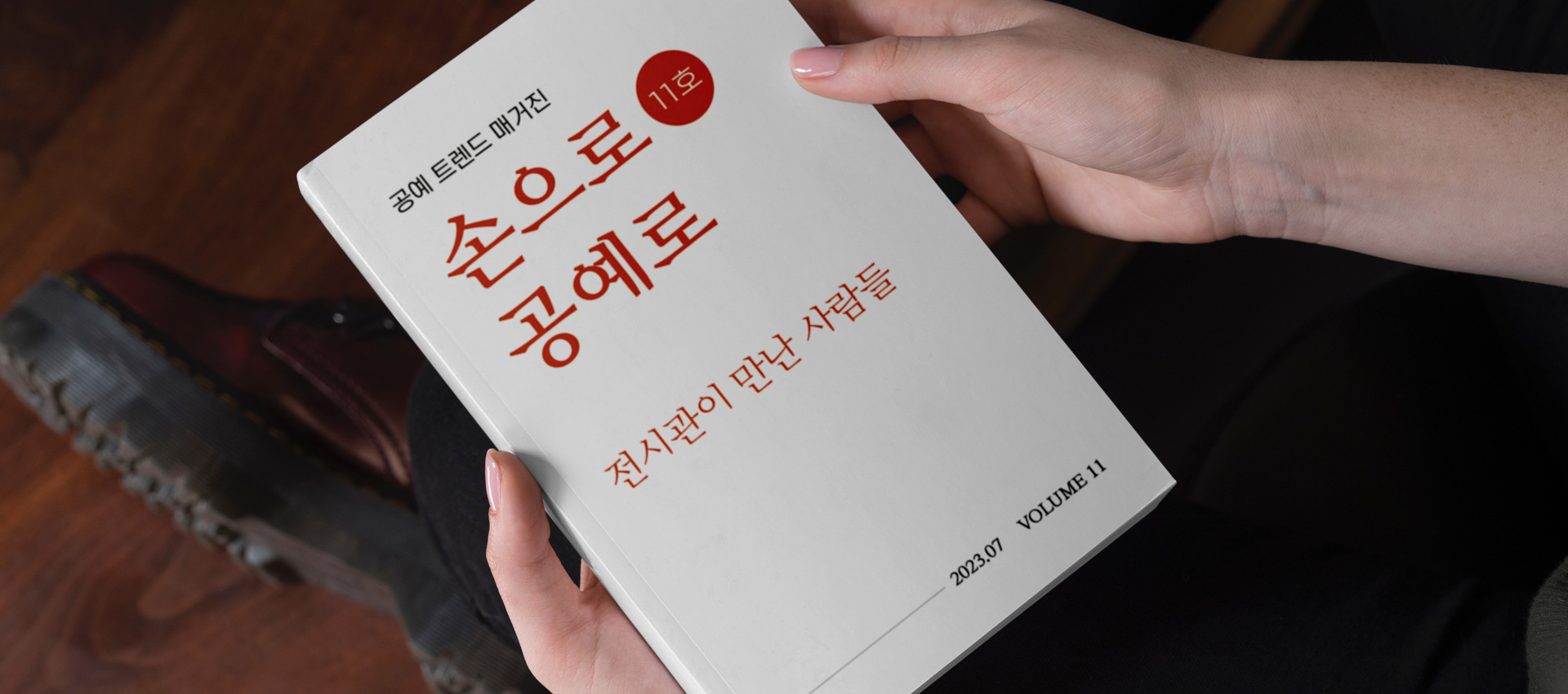
전주공예명조체 — 전주공예품전시관에서 배포하는 무료 폰트입니다. 지역 공예인의 창작 활동을 돕겠다는 취지로 만든, 현대적으로 다듬은 본문용 명조 서체
한국전통문화전당 전주공예품전시관이 전주수공예거점도시 사업의 하나로 2023년에 내놓은 서체입니다. 지역 공예인의 창작 활동을 돕고 공예산업의 정체성을 세우겠다는 것이 사업 취지였습니다. 이름 때문에 전통 공예품의 형태를 본떴으리라 짐작하기 쉽지만, 특정 공예품에서 조형을 가져왔다는 설명은 공개 자료에서 확인되지 않습니다.
형태는 파일에서 직접 재어 봤습니다. 세로획이 가로획의 2.1배로 부리 계열의 성격이 뚜렷하고, 받침이 붙을 때 글자 높이가 눈에 띄게 달라지는 탈네모틀 구조입니다. 명조이면서 네모틀을 벗어난 조합은 흔치 않아서, 글줄이 가지런히 떨어지기보다 손으로 쓴 듯한 리듬을 냅니다. 현대 한글 11,172자를 모두 담았습니다.